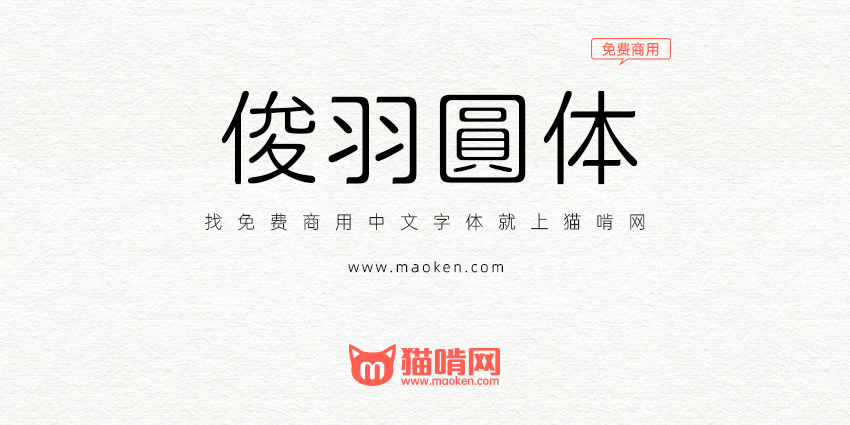
字体名称:俊羽圓體 | 字体版本:Version 1.011 2022.05.03 |
字体作者:Max(中国台湾) | 字体字重:5个 |
俊羽圆体是基于粉圆字体修改而成。原本的构想是要挑战把粉圆改成羽逸体,发现工程有点浩大,目前是半成品,聊胜于无,大家可以试用看看。也欢迎勇者接续修改,可以把修改好的寄给Max,或直接在再开出新的字型名称。
与粉圆体的差别在,横线右上和左下角,有三角形的衬线,笔触由原本的圆头换成方头,工程浩大在一个字、一个字改,旷日费时。
繁体没有吗
有些Regular中的英文數字樣例,原作者做得不怎麼好